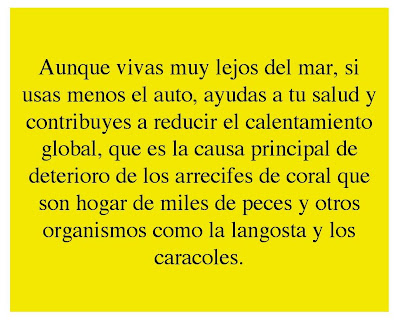
La tipografía que utilice puede hacer que su mensaje llegue rápidamente o, por el contrario, puede debilitar o contradecir el significado de su escrito. El tipo de letra puede invocar cierto estilo, transmitir prestigio y calidad, hablar de un buen negocio, o dar la idea de que se trata de un producto de actualidad o que respeta una vieja tradición.
Según Graham Clifford, diseñador gráfico de Chiat/Day/Mojo, «La tipografía transmite mensajes "ocultos"-el "tono de voz" en el que se presenta el texto-. Los tipos poseen esta habilidad única para gritar, susurrar, persuadir, preguntar o solicitar.» Y a mi parecer tiene toda la razón!!!
Cuando elija una tipografía tenga en cuenta:
- la naturaleza del producto
- el tipo de cliente al que se dirige
- las características del anuncio que va a hacer (longitud del texto, ilustración, expectativas de venta)
- las publicaciones en que va aparecer su anuncio
- las tipografías que están de moda
- y sobre todo, debe considerar la legibilidad de los caracteres tipográficos que elija.
La mayoría de las personas se sienten mas interesados en un texto impreso cuando tiene algún tipo que les resulte familiar, es decir que estén acostumbrados a ver: Century, Caslon, Times, Baskerville, Futura, Garamond y Goudy.
Tanto como sea posible, disponga su texto en líneas horizontales tradicionales. Las tipografías impresas en espiral, curvas o en diagonal son difíciles de leer y en consecuencia, no atraen al lector.
Utilice tinta negra sobre fondo blanco o por lo menos, letras oscuras sobre un fondo pálido. A continuación una lista de las combinaciones de colores por orden de legibilidad decreciente:
- negro sobre blanco
- gris sobre blanco
- azul sobre blanco
- negro sobre amarillo
- rojo sobre amarillo
- rojo sobre blanco
- verde sobre rojo
- naranja sobre negro
- naranja sobre blanco
- rojo sobre verde
- negro sobre violeta
Por regla general, un anuncio no deberá tener más de dos tipos de letra diferentes y, decididamente, no más de tres. Un anuncio que contenga demasiados tipos de letra exige un gran esfuerzo al ojo del lector.
Y como dice Stephen Baker en su libro Advertising Layout and Art Direction: «El tipo de letra puede invitar a leer o no».